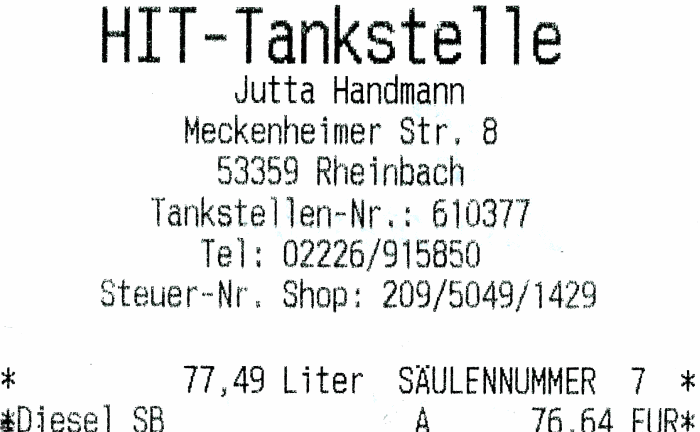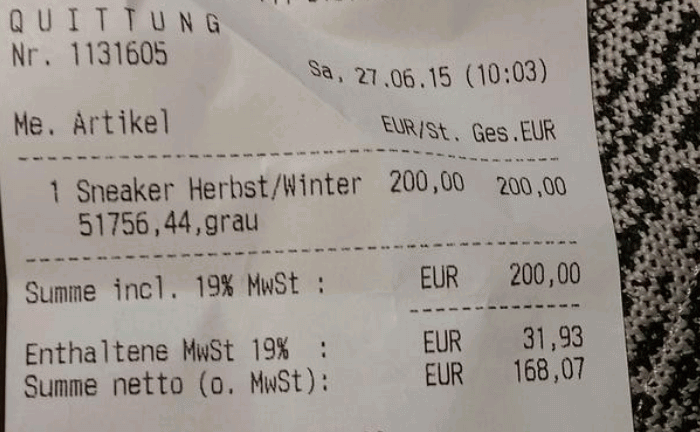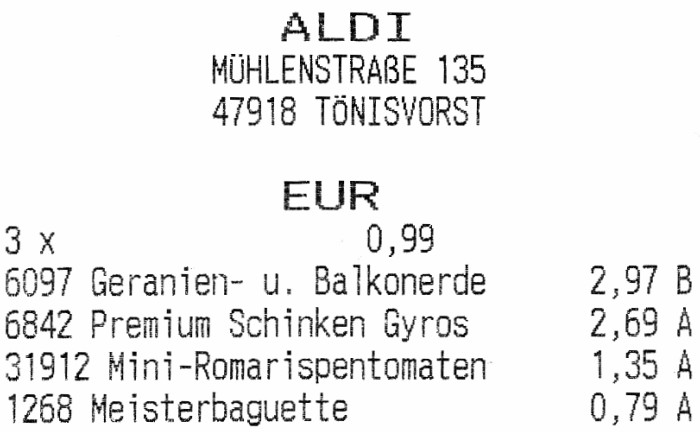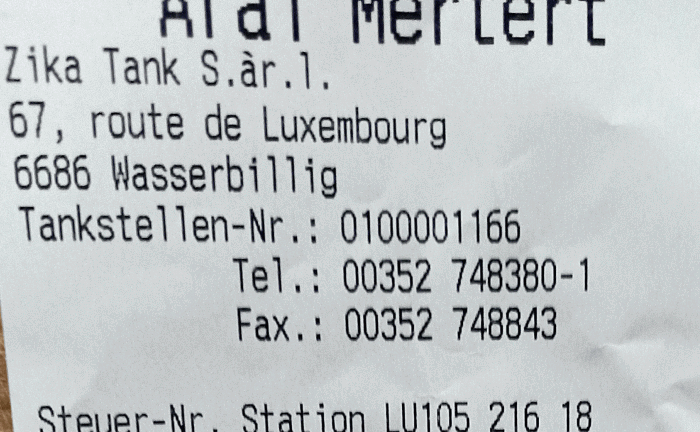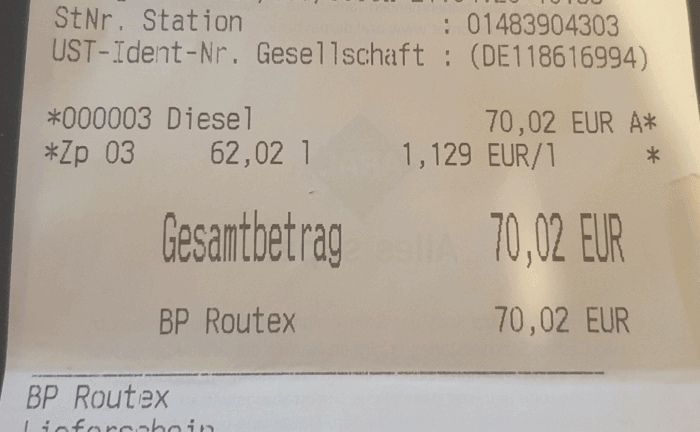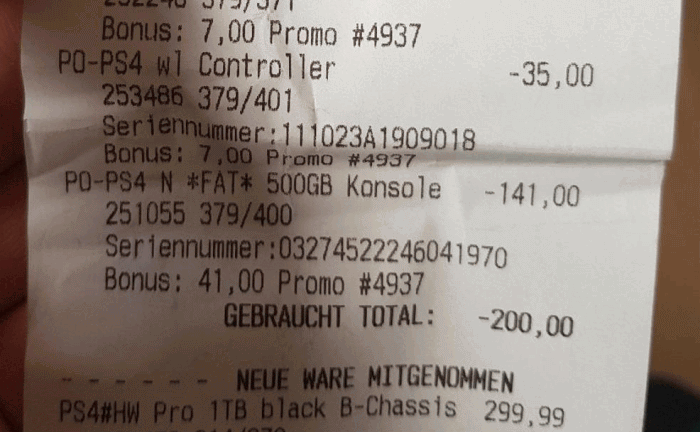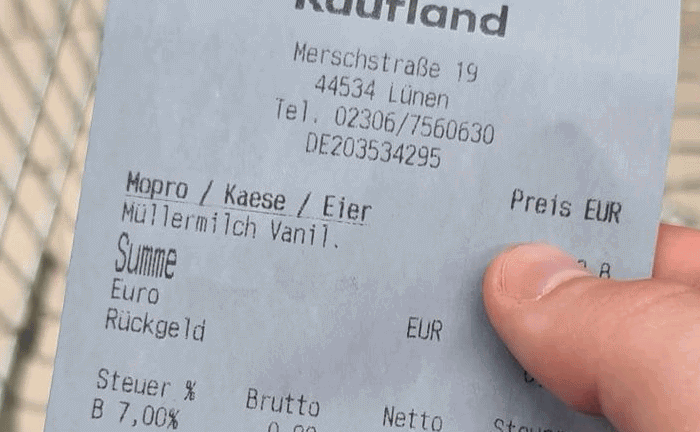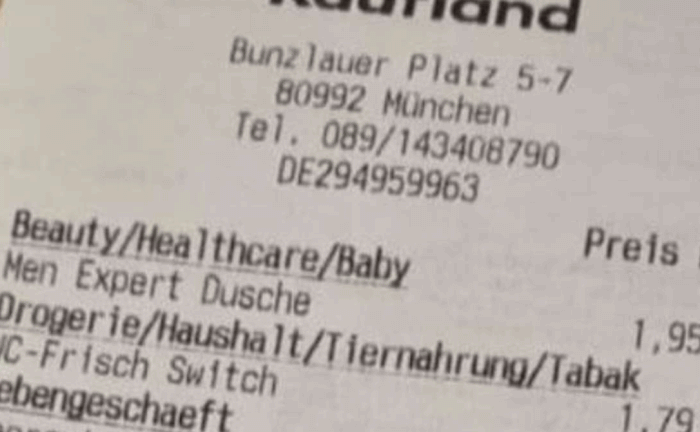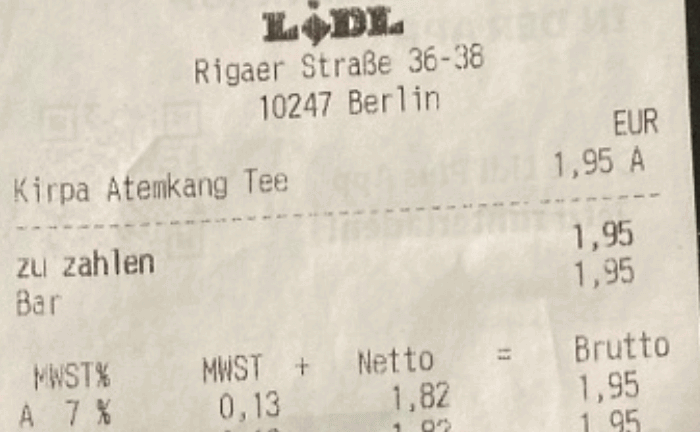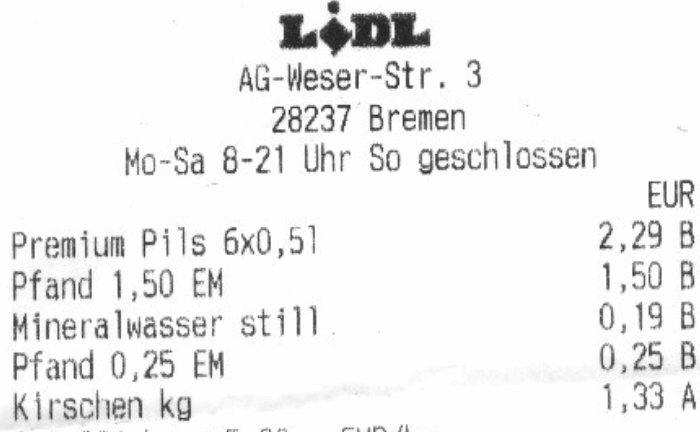
Sehr gängige Rechnung-Schriftart für Thermodrucker
eine Schriftart, die normalerweise für Quittungen von Restaurants/Geschäften/Supermärkten/Tankstellen verwendet wird
Sehr gängige Kassenbeleg-Schriftart für Thermodrucker
auf dem Computerbildschirm angezeigt
gedrucktes Sample von der Schriftart⤴ ( Kassenbon-Schriftart auf Abseits-Quittung )
gedrucktes Sample von der Schriftart⤴ ( Kassenbon-Schriftart auf Aldi-Quittung )
gedrucktes Sample von der Schriftart⤴ ( Kassenbon-Schriftart auf Aral-Quittung )
gedrucktes Sample von der Schriftart⤴ ( Kassenbon-Schriftart auf Gamestop-Quittung )
gedrucktes Sample von der Schriftart⤴ ( Kassenbon-Schriftart auf Kaufland-Supermarkt-Quittung )
gedrucktes Sample von der Schriftart⤴ ( Kassenbon-Schriftart auf Kaufland-Quittung )
gedrucktes Sample von der Schriftart⤴ ( Kassenbon-Schriftart auf Lidl-Supermarkt-Quittung )
gedrucktes Sample von der Schriftart⤴ ( Kassenbon-Schriftart auf Lidl-Quittung )
gedrucktes Sample von der Schriftart⤴ ( Kassenbon-Schriftart auf MediaMarkt-Quittung )
gedrucktes Muster von der Schriftart⤴ ( Kassenbon-Schriftart auf OMV-Tankstelle-Beleg)
gedrucktes Sample von der Schriftart⤴ ( Kassenbon-Schriftart auf Rewe-Supermarkt-Beleg)
gedrucktes Sample von der Schriftart⤴ ( Kassenbon-Schriftart auf Saturn-Beleg)
gedrucktes Sample von der Schriftart⤴ ( Kassenbon-Schriftart auf Saturn-Quittung)
gedrucktes Sample von der Schriftart⤴ ( Kassenbon-Schriftart auf SB-Tankstelle-Quittung)
gedrucktes Sample von der Schriftart⤴ ( Kassenbon-Schriftart auf Shell-Tankstelle-Quittung)
gedrucktes Sample von der Schriftart⤴ ( Kassenbon-Schriftart auf HIT-Tankstelle-Beleg)
gedrucktes Sample von der Schriftart⤴ ( Kassenbon-Schriftart auf Shell-Tankstelle-Quittung)